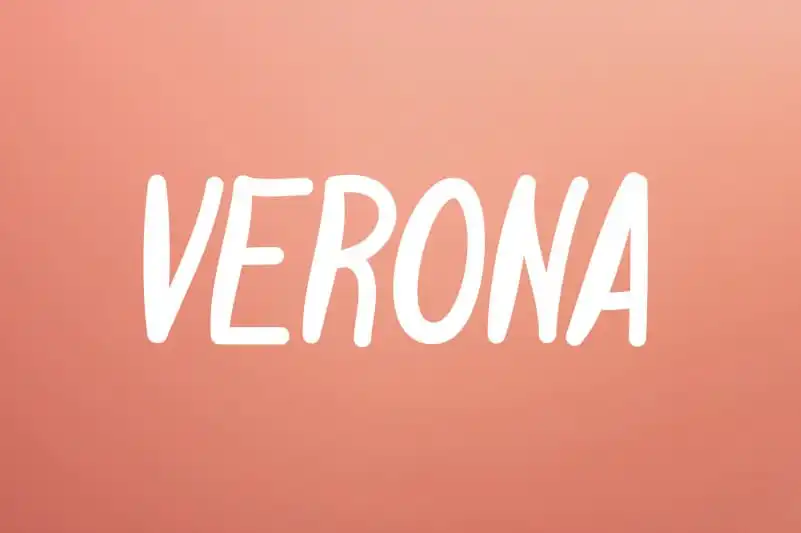
Verona Display Font
A Verona Display Font é uma escolha ideal para qualquer ocasião, seja ela formal ou informal. Ela combina elegância com facilidade de leitura e escrita, tornando-se uma opção favorita tanto para designers profissionais quanto para quem busca um estilo autêntico em seu trabalho diário. A fonte é especialmente atraente quando usada em aplicativos digitais e impressos, oferecendo legibilidade notável para seus caracteres script. Com sua graça natural e sutileza, Verona Display não apenas ajuda a destacar suas criações visuais, mas também torna o processo de trabalho mais envolvente e gratificante. Para quem procura um estilo autêntico em suas fontes, essa é uma opção perfeita para capturar o brilho da sua personalidade através de cada projeto. Como a fonte é especialmente adequada às fontes escritas à mão, ela pode ser particularmente útil para designers que valorizam esse aspecto único do design gráfico.